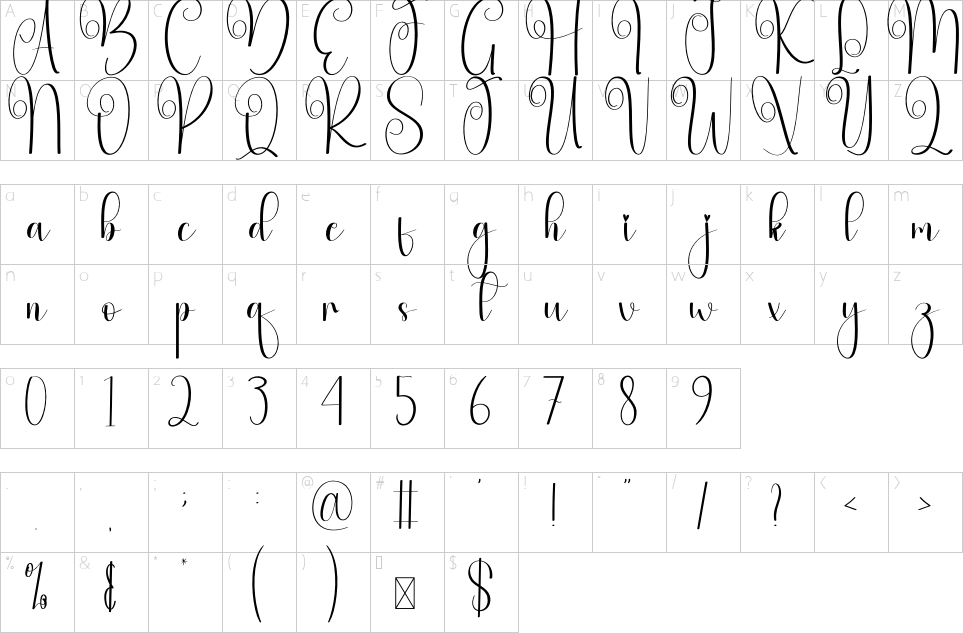
A fonte ‘Santa Bestieday’ é um presente para designers e criativos que buscam uma fonte elegante e moderna para suas criações digitais. Desenhada por William Jhordy, esta fonte foi projetada para oferecer um equilíbrio perfeito entre funcionalidade e apelo visual, tornando-a uma escolha atraente para designers gráficos e desenvolvedores de websites. Disponível tanto para usuários de Windows quanto de Mac, ‘Santa Bestieday’ oferece uma paleta de opções que pode ser facilmente adaptada às suas necessidades de design. Com uma grande quantidade de downloads, percebemos que os criativos do Brasil e do mundo reconhecem a qualidade desta fonte, e agora você também pode adquiri-la para enriquecer seus trabalhos.